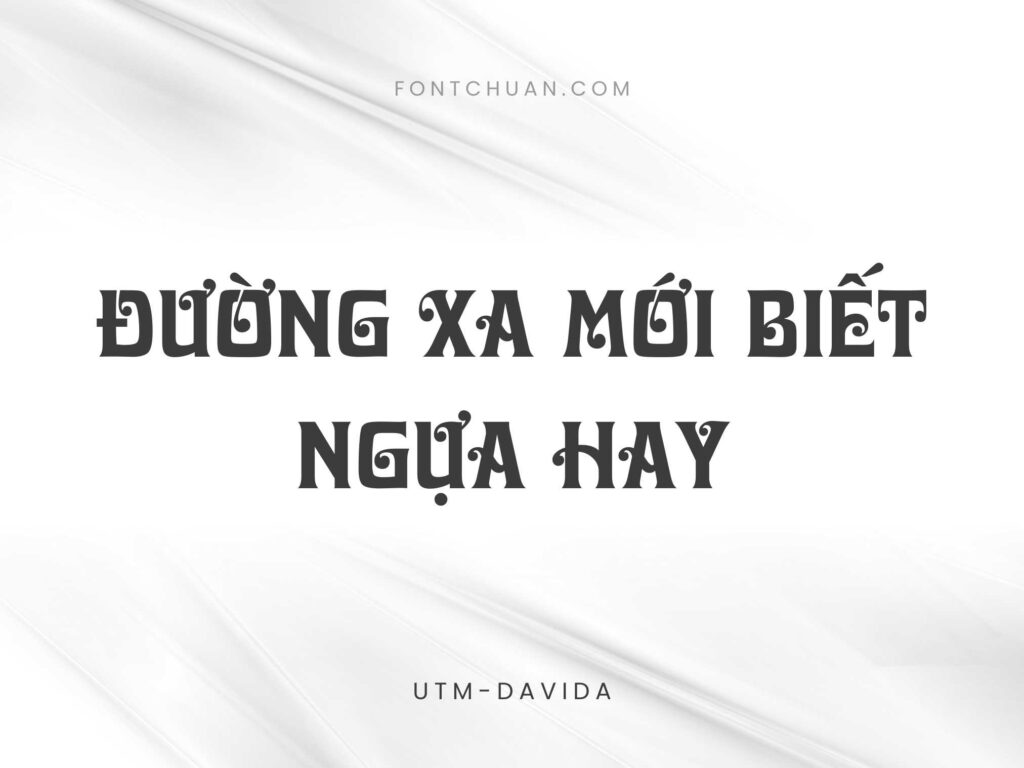
Font UTM Davida Việt Hóa là một kiểu chữ serif độc đáo, mang phong cách cổ điển nhưng vẫn giữ được nét hiện đại. Với các nét chữ thanh mảnh, độ dày linh hoạt và đường nét mềm mại, font này là lựa chọn hoàn hảo cho các thiết kế mang phong cách sang trọng, quý phái.
Font này đã được Việt hóa để hỗ trợ đầy đủ tiếng Việt bởi Thiên Minh, ngoài ra còn hỗ trợ hơn 200 ngôn ngữ khác. Thành viên của Font Chuẩn đã sưu tầm và chọn lọc font này nhằm đáp ứng nhu cầu của người dùng trong thiết kế và ứng dụng thực tế. Font có đặc điểm nổi bật với đường nét tinh tế, phù hợp với các dự án như thiết kế logo, bìa sách, quảng cáo thời trang và nhiều lĩnh vực khác.